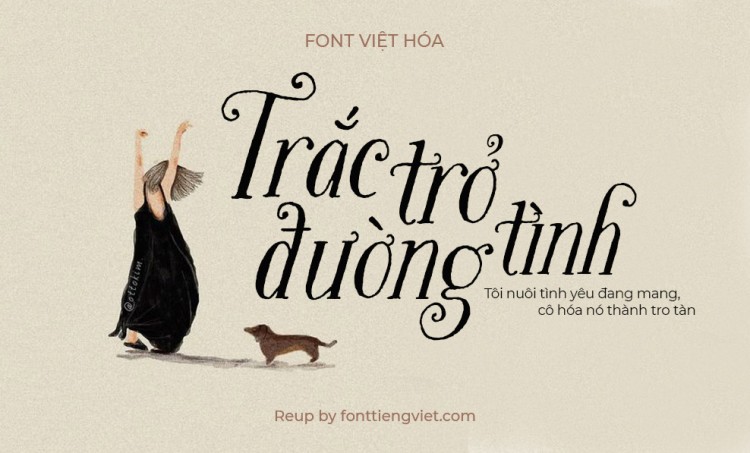
Font việt hóa FS Bookeye Sadie Roman
Font việt hóa FS Bookeye Sadie Roman – Nét chữ cổ điển đầy tinh tế
Trong thế giới thiết kế đồ họa, việc lựa chọn một Font Miễn Phí phù hợp là yếu tố then chốt để tạo nên linh hồn cho tác phẩm. Font việt hóa FS Bookeye Sadie Roman nổi lên như một sự lựa chọn hoàn hảo cho những ai yêu thích phong cách cổ điển, sang trọng nhưng vẫn giữ được nét hiện đại. Bộ font này không chỉ mang lại giá trị thẩm mỹ cao mà còn hỗ trợ đầy đủ bảng mã tiếng Việt, giúp các bạn học sinh và giáo viên dễ dàng ứng dụng vào việc thiết kế bài giảng hoặc trình bày tài liệu học tập một cách chuyên nghiệp.
Khám phá vẻ đẹp độc đáo của Font việt hóa FS Bookeye Sadie Roman
Được lấy cảm hứng từ những bản in khắc gỗ thế kỷ 18, Font việt hóa FS Bookeye Sadie Roman mang trong mình những đường nét uốn lượn mềm mại và cấu trúc chữ chặt chẽ. Điểm đặc biệt của phông chữ này chính là sự kết hợp giữa nét thanh và nét đậm một cách hài hòa, tạo nên cảm giác hoài cổ nhưng cực kỳ dễ đọc. Đây là một biến thể trong họ Bookeye nổi tiếng, vốn được các nhà thiết kế tin dùng cho các bìa sách, nhãn hàng thủ công và các ấn phẩm nghệ thuật đòi hỏi sự tỉ mỉ.
Ứng dụng thực tế trong giáo dục và thiết kế
Với các bạn học sinh, sử dụng Font việt hóa FS Bookeye Sadie Roman giúp các bài báo tường hay tiểu luận trở nên nổi bật hơn. Trong khi đó, các thầy cô có thể dùng font này để làm tiêu đề cho các trang giáo án điện tử, tạo ấn tượng thị giác mạnh mẽ cho người xem. Khả năng hiển thị sắc nét của nó đảm bảo rằng ngay cả ở kích thước nhỏ, nội dung vẫn rõ ràng và không bị nhòe.